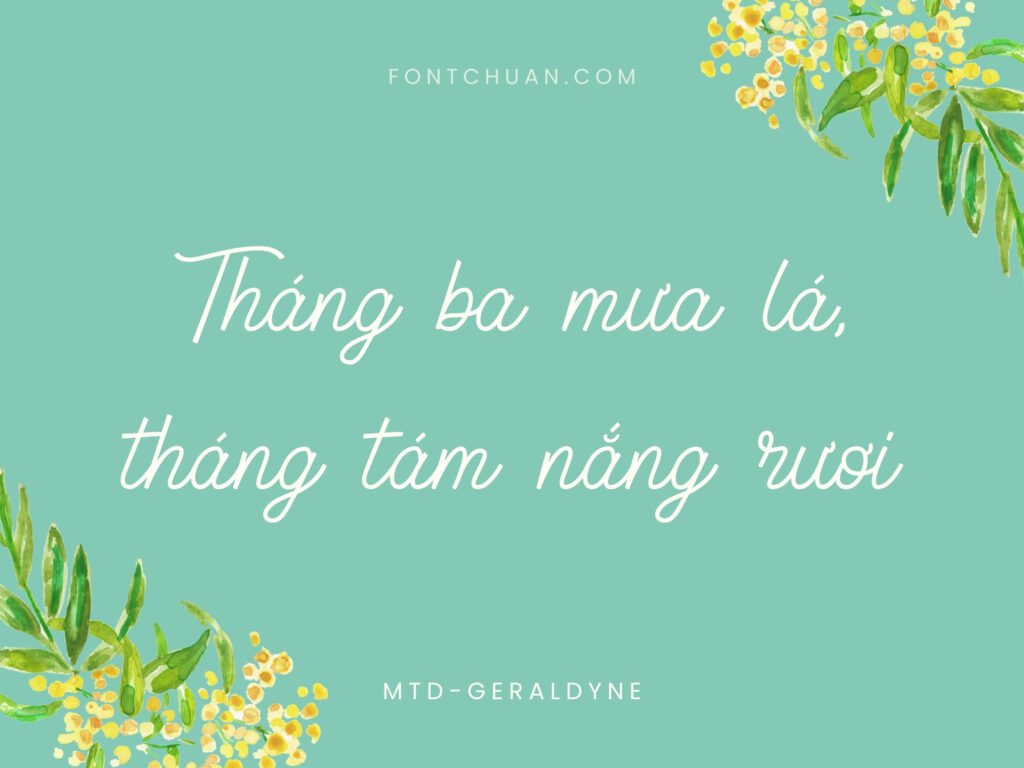
Font MTD Geraldyne Việt Hóa
Font MTD Geraldyne là một phông chữ script thanh lịch, được thiết kế với phong cách viết tay mềm mại và uyển chuyển. Font đã được Việt hóa bởi Mộc Hạ, hỗ trợ tiếng Việt và hơn 90 ngôn ngữ khác, giúp mở rộng khả năng ứng dụng trong các thiết kế đa ngôn ngữ. Đây là một trong những phông chữ được cộng đồng thiết kế đánh giá cao và ứng dụng trong nhiều dự án sáng tạo, đáp ứng nhu cầu đa dạng của người dùng.
MTD Geraldyne nổi bật với các đường nét tinh tế, mang đến cảm giác sang trọng và hiện đại. Font rất phù hợp cho các thiết kế logo, tiêu đề tạp chí, thương hiệu thời trang, thiệp mời và các ấn phẩm đòi hỏi sự tinh tế và chuyên nghiệp. Các ngành nghề phù hợp bao gồm quảng cáo, giáo dục, công nghệ, thiệp cưới và ảnh cưới. Font này cũng lý tưởng cho các sự kiện như Tết, Giáng sinh, Valentine và các lễ hội khác.